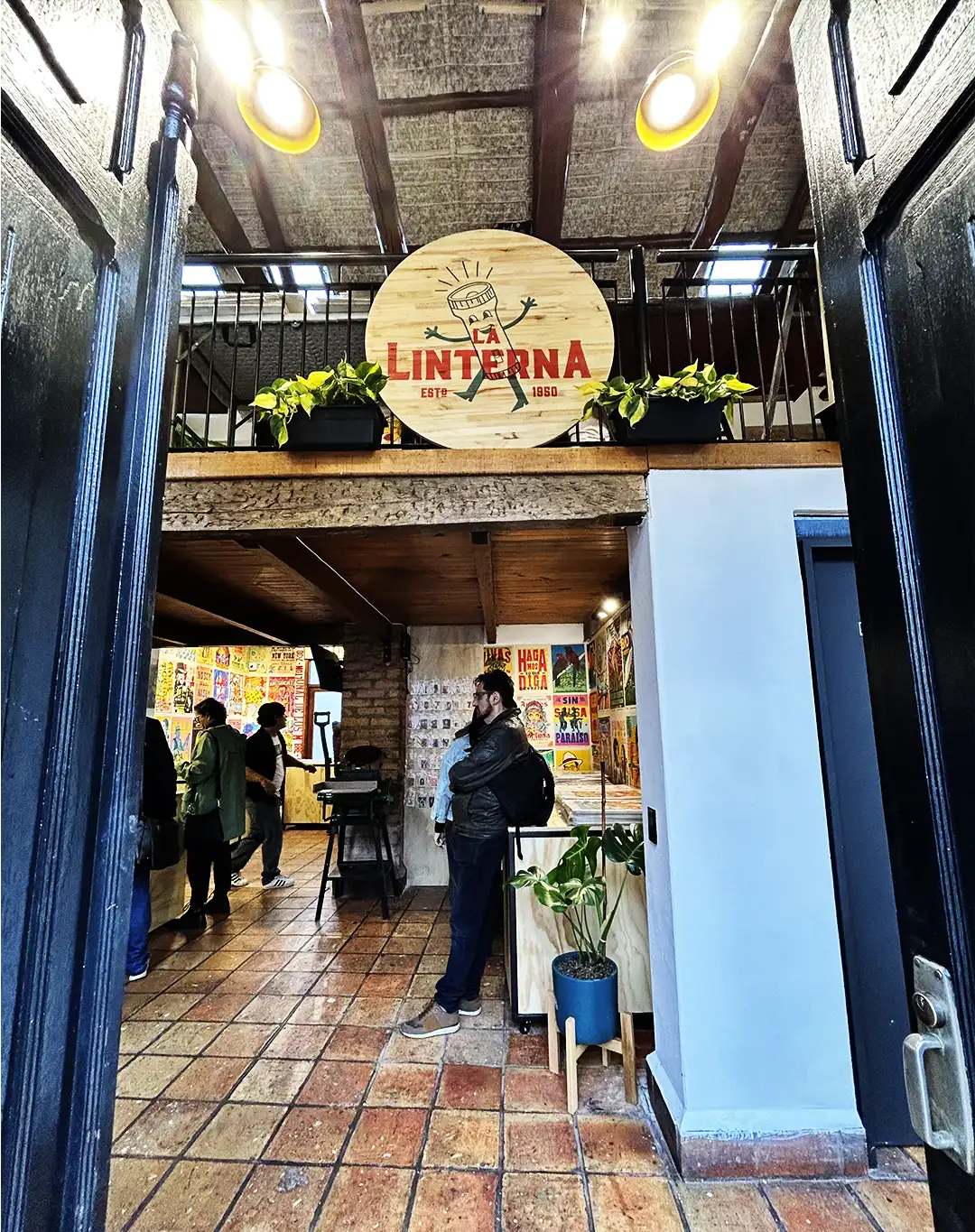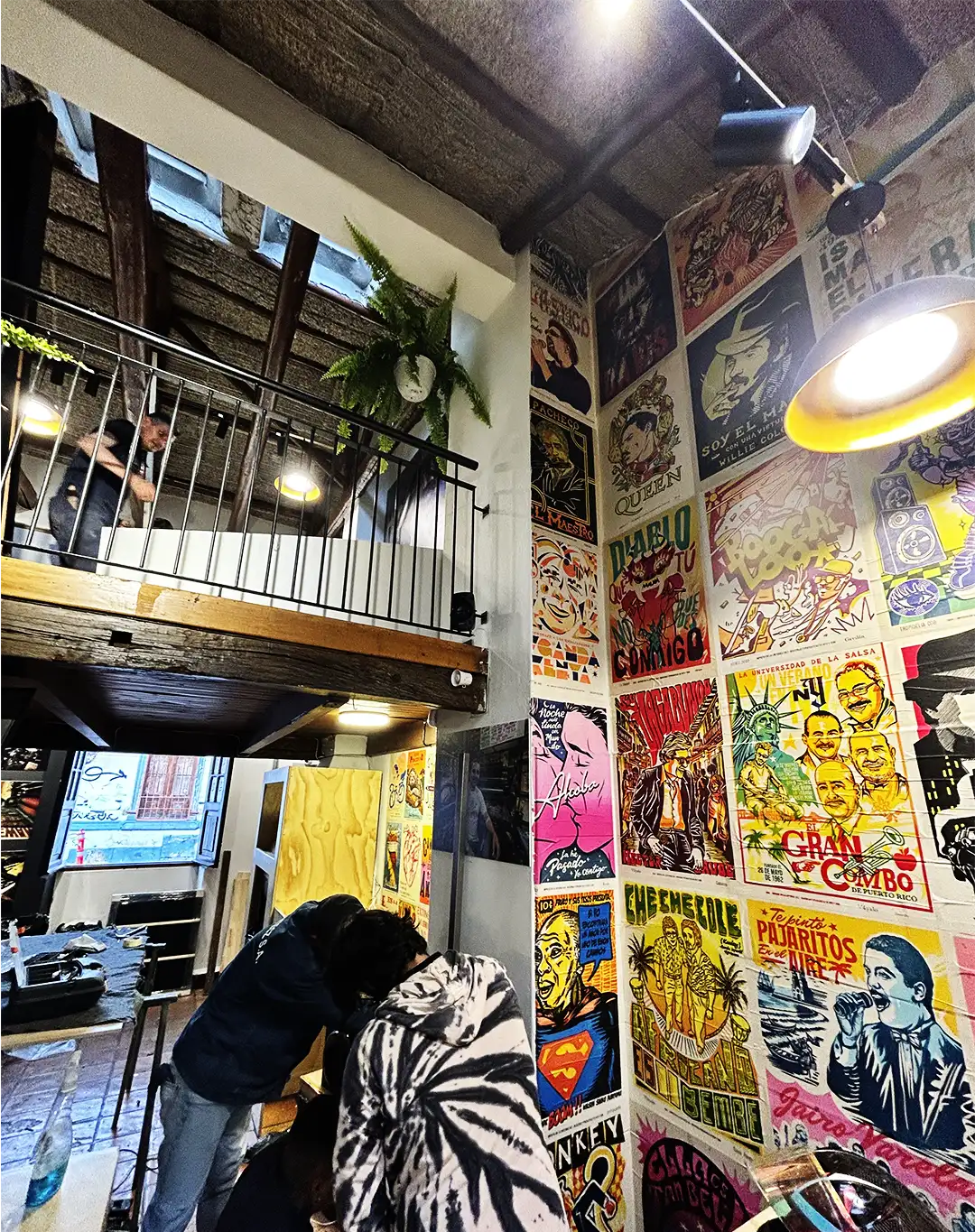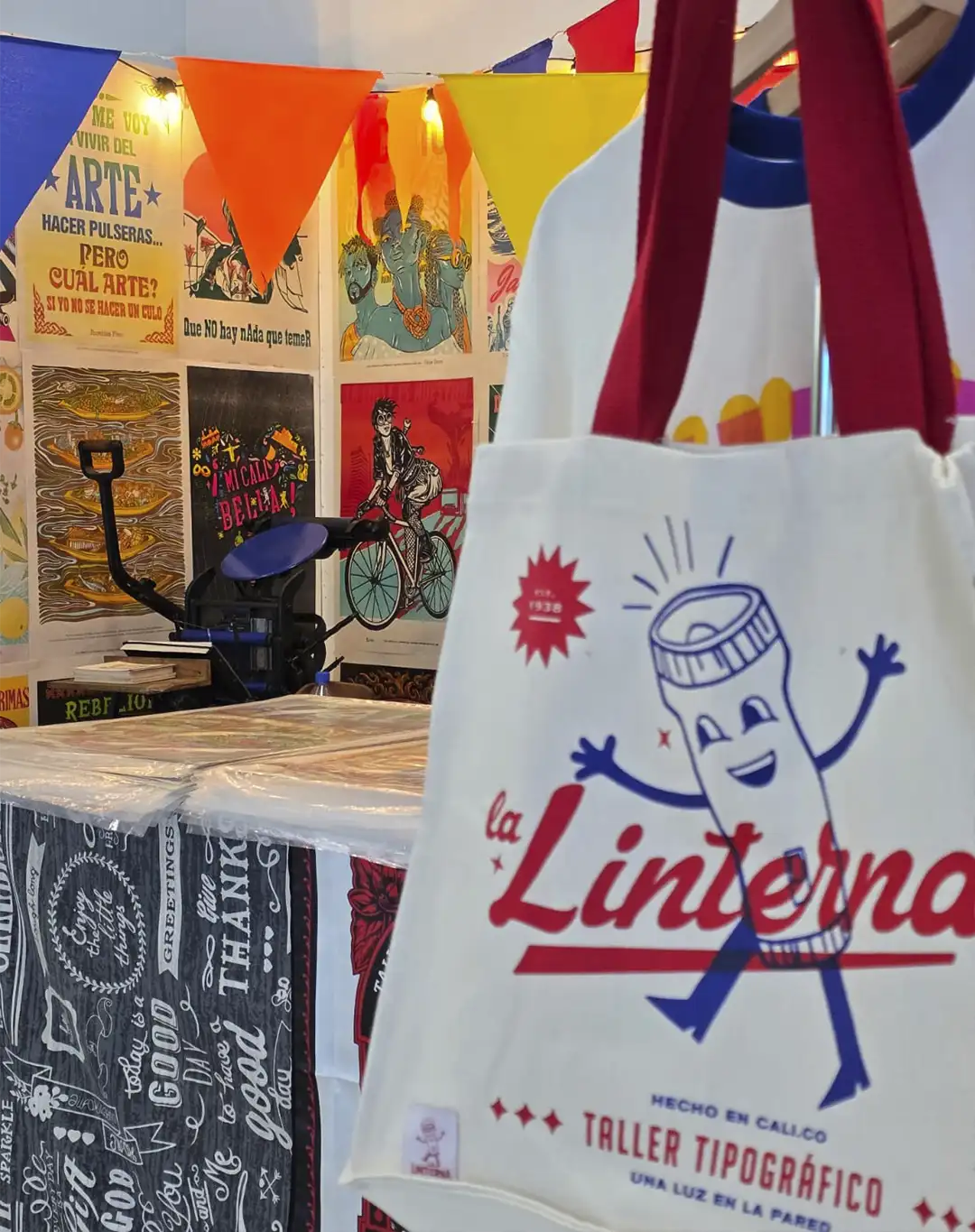
La Linterna
La Linterna: de San Antonio para el mundo
En un rincón del centro de Bogotá, replicando la esencia de su hogar en Cali, se alza La Linterna, taller tipográfico fundado en 1934 donde el ladrillo y el papel conservan la memoria popular colombiana. Esta imprenta artesanal de carteles de salsa y rock, usando tipos móviles y linograbado, transformó su lucha por sobrevivir en una estrategia cultural.
En una esquina empinada de La Candelaria, una puerta de madera alta deja ver las paredes del interior. Sin embargo, para una miope, el escenario era el de una lucha campal entre las paredes blancas y la parranda de colores de los carteles apretados que buscan lucirse sobre ella. Cinco pasos adelante y una limpiada a los lentes de las gafas, terminan de darle forma a esa casa de ladrillos color caoba.
Tiene una salita iluminada con unas plantas cuyos colores se funden con la riqueza cromática de los carteles neón. Unos están a punto de empezar una revolución, otros repiten frases célebres de Facundo Cabral, cantan versos de Rubén Blades, Héctor Lavoe y gritan en acento Caleño que “Cali es Capital Mundial de la Salsa”. En ese rincón del centro de Bogotá, el papel, el color y la tinta se reúnen para conservar la memoria popular de Colombia en cada trazo. Esa es La Linterna.
Taller de impresión tipográfica fundado en 1934 en el barrio San Antonio de Cali, en sus inicios la Linterna se dedicaba a la creación artesanal de carteles publicitarios y propaganda política empleando la técnica de linograbado y tipos móviles. Este sistema combinaba el grabado en linóleo para las imágenes y los tipos móviles (letras de metal) para componer el texto de manera uniforme.
A finales de los setenta, La Linterna estuvo a tope. Incluso, enviaban carteles a Medellín y Bogotá. Los impresores tenían doble turno y se capacitaban en 15 días. Las máquinas muchas veces iniciaban su trabajo cerca de las 6:00 am hasta la medianoche. Sin embargo, a principios del nuevo siglo y con los avances de la producción comercial masiva, las horas de producción, las máquinas y las manos de los maestros fueron dejadas al olvido hasta el punto de casi desaparecer.
Hoy, casi un siglo después, La Linterna no es un vestigio del pasado ni un museo en funcionamiento. Es una empresa cultural viva con dos sedes: Cali y Bogotá, más de treinta personas vinculadas directa o indirectamente, una marca de ropa en expansión y un proyecto internacional que ya opera desde Estados Unidos. Algo que dejó entrever que lejos de ser un taller cultural rescatado levantado entre sus cenizas, es un organismo vivo cuyas personas involucradas entendió las dinámicas de trabajo, el arte y el esfuerzo.
Los maestros: la raíz que los sostiene todo
Para hablar de La Linterna, hay que hablar de los que siempre estuvieron ahí. Antes de las fotografías, la música y los parches de diseñadores: los maestros Héctor, Jaime y Olmedo, el corazón del taller, los que junto con los artistas y colaboradores que aún trabajan con ellos le dan vida a La Linterna. Actualmente, sobre ellos recae la administración, la producción y, además, la formación de nuevos impresores para la continuidad técnica del proyecto.
“Muchos se quedan con nuestros inicios y desconocen la profundidad de lo que somos hoy”, dice el maestro Héctor. “La parte administrativa funciona de forma piramidal: Olmedo, Jaime y yo estamos en la raíz, y de ahí se desprenden las demás ramas” añade.
Hoy ya son diecisiete con contrato, sueldo y prestaciones, además de un grupo de colaboradores externos en diseño, redes y gestión cultural y treinta en general que giran directa en indirectamente alrededor de La Linterna, que se ha convertido en un foco cultural, no solo por los maestros, sino por los artistas que allí brillan como, por ejemplo, el profesor Carrillo. Un maestro que hoy representa uno de los pilares del taller. Es el director de arte y la mano que se encarga de recibir las propuestas que llegan, lo que ha sido fundamental para el crecimiento del proyecto.
A eso se suma un relevo generacional activo: ayudantes que aprenden directamente de los maestros, hijos y nietos que se forman en el grabado y el manejo de las máquinas, y jóvenes diseñadores que traducen nuevas estéticas al lenguaje técnico del taller. Ese conocimiento no se enseña en universidades. Se transmite en el hacer, en la repetición paciente, en el error. Por eso, La Linterna funciona también como hogar, taller y escuela informal: un espacio donde artistas y diseñadores aprenden a pensar desde la imprenta, entendiendo las limitaciones y posibilidades de máquinas que datan de finales del siglo XIX.
Hace ocho años, eran más o menos ocho personas las que estaban trabajando con los maestros: “Un grupo grande de diseñadores caleños a quienes no podemos quitarles el nombre, porque pusieron su grano de arena para que La Linterna sea lo que es hoy. Se pusieron el uniforme, no cobraron y, de manera desinteresada, aportaron su creación. De ahí nació este nuevo auge de La Linterna” recuerda Héctor.
Del taller cerrado a toda Cali
A unas cuantas cuadras, en la calle donde aún hoy se conserva la sede caleña, La Linterna era un taller pequeño a puerta cerrada, donde el mundo secreto y obsoleto de la impresión de carteles moría poco a poco, junto con las esperanzas de los maestros que allí trabajaban.